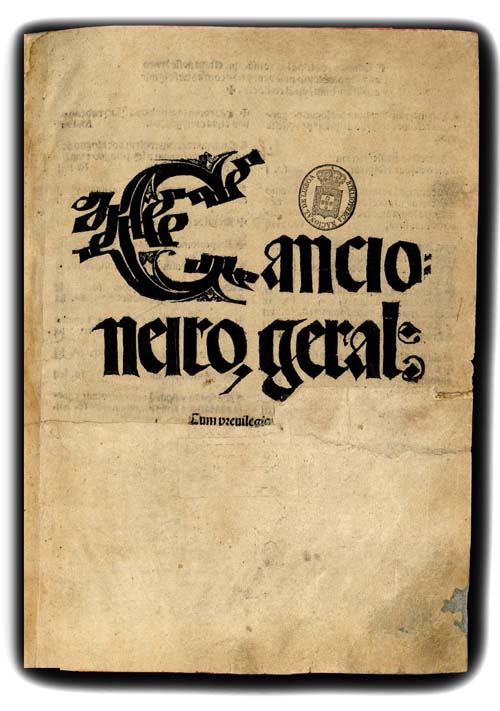
Hermann Kempis (Hermão de Campos)No ano de 1509 tinha-se estabelecido, em Setúbal, outro impressor alemão: Hermann von Kempen, conhecido por Hermão de Kempis ou Hermão de Campos.Começa por imprimir os Estatutos da Ordem de Santiago. Em associação com Valentim Fernandes, Hermão de Kempis imprime Ho compromisso e regimento dos officiaes da sancta confraria da Mesericordia. Ho Flos Sanctorum em Linguagem Português foi editado em 1513 por Hermam de Campos e Roberto Rabelo. Os Flores Sanctorum, apesar do seu nome significar Florilégio de Santos, incluíam também comentários ao evangelho. A obra Bosco Deleytoso Solitario foi igualmente impressa por Hermão de Campos, em 1515. Em 1516, segue-se o Cancioneiro geral: cum preuilegio / [Foy ordenado e eme[n]dado por Garcia de Reesende fidalguo da casa del Rey nosso senhor e escriuam da fazenda do principe]. - Almeyrym e acabouse na muyto nobre e sempre leall cidade de Lixboa : per Hermã de Cãmpos, 28 Sete[m]bro 1516.
Esta impressão está disponível online em http://purl.pt/12096 O nome de Garcia de Resende aparece no colofão. Título em caracteres xilográfios. |